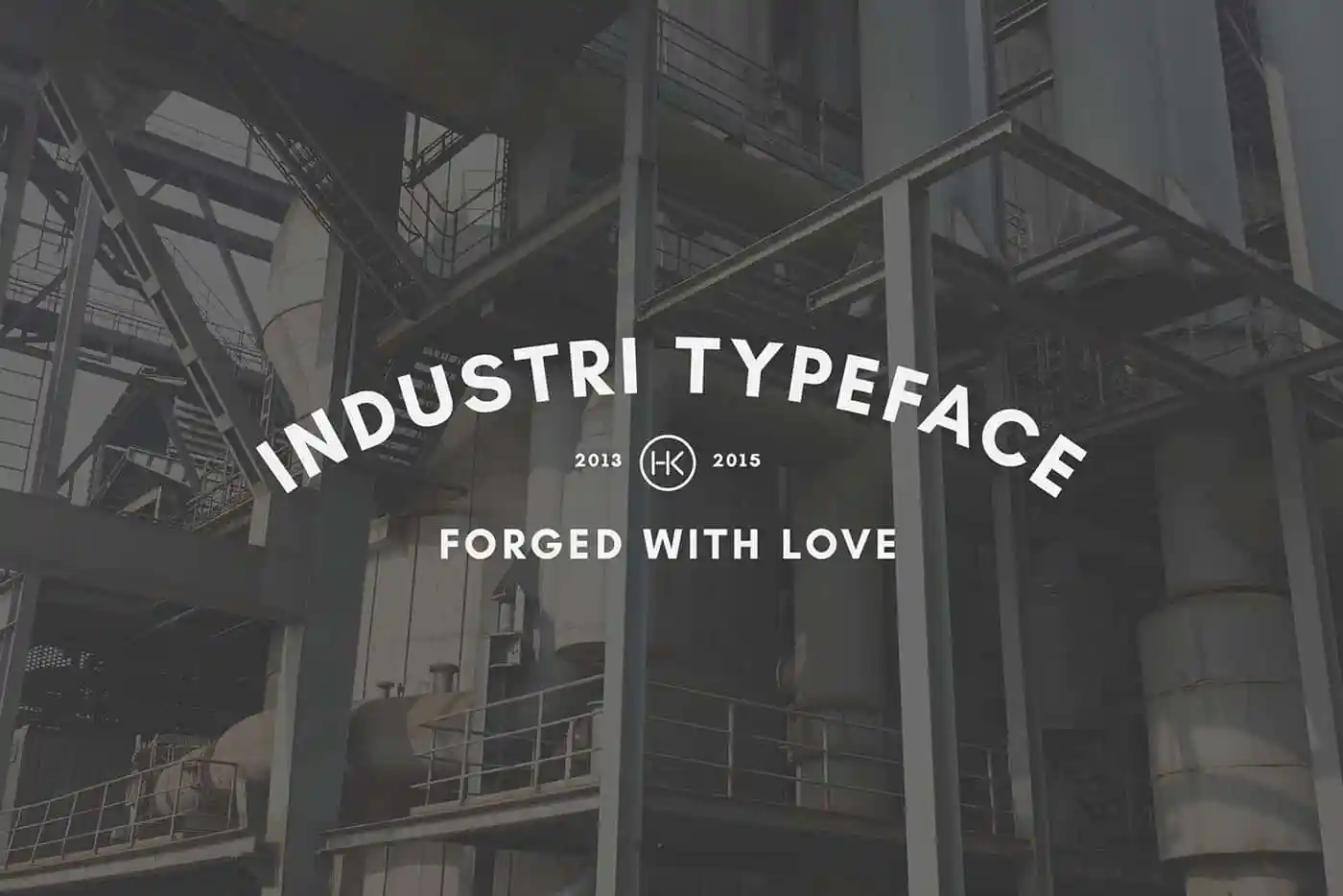
Industri Typeface – Fonte Grátis
Industri Typeface
Introduzimos à você a fonte industrial ideal para seus projetos digitais. Industri é uma robusta fonte sans-serif perfeita para logotipos e headlines, com um peso forte que destaca sua mensagem de forma impressionante. Esta fonte é perfeitamente adequada para aplicativos onde uma aparência moderna e atraente são essenciais. Se você está à procura de algo robusto, sólido e sem detalhes superfluos, Industri é a escolha certa. Baixe-a agora e experimente sua eficácia!